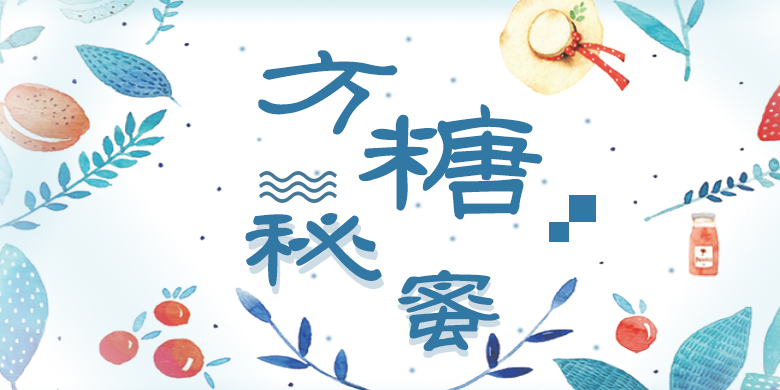
方正字汇-方糖秘蜜体简体方正字汇-方糖秘蜜体品牌:方正字汇,方正字体下载,方正字库,方正字体, 设计师:梁健强, 发行时间:2019, 字库编码:大陆简体(GB2312-80), 分类:创意书写,标签:个性、书法、手写 、毛笔字体书法,简约,古典,2019新字体,字体介绍:方糖秘蜜体结构规整,字形偏扁,有着隶书的意趣,继承了传统隶书特征,结构更现代,显得轻盈温和。字体用笔均匀、笔画却存筋藏势。适用于各种具有历史和传统文化的语境,如博物馆的展览视觉和宣传品设计。POP字体下载官网下载 发布日期 2019年11月17日 发布于 书法字体 上篇文章: 汉仪昌黎宋刻本(原版)W 下篇文章: 汉仪寒石粗体简 发表回复 取消回复要发表评论,您必须先登录。